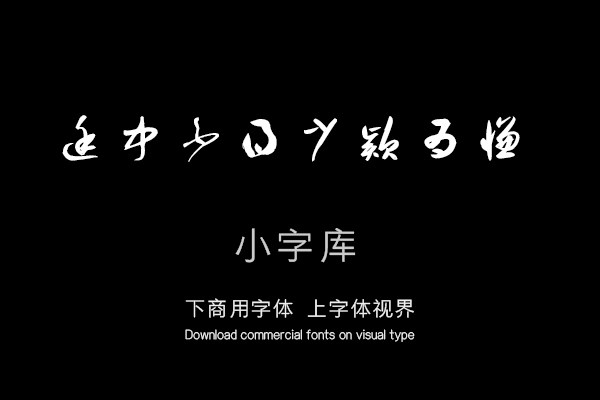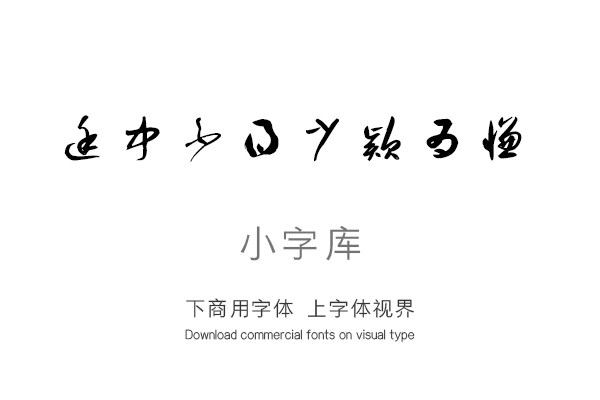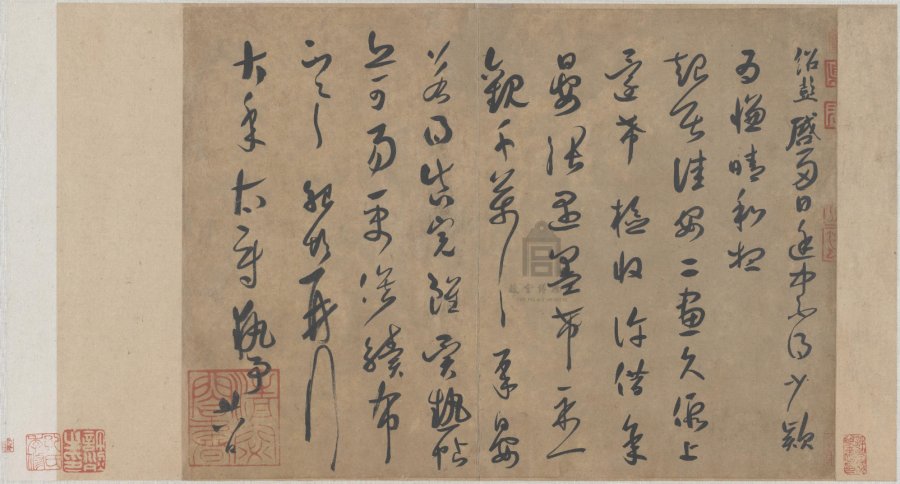
汉标薛绍彭大年帖
《汉标薛绍彭大年帖》是一款根据宋代薛绍彭经典书法作品《大年帖》此帖名也作《晴和帖》,经过再次调整制作的小字库,该小字库共收录了该真迹作品中约97个字体。
绍彭启:多日廷中不得少款为慊。晴和,想起居佳安。二画久假,上还,希检收。许借承晏、张遇墨,希示一观,千万,千万!承晏若得真完,虽《异热帖》亦可易。更俟续布,不具。绍彭再拜,大年太尉执事。廿八日。